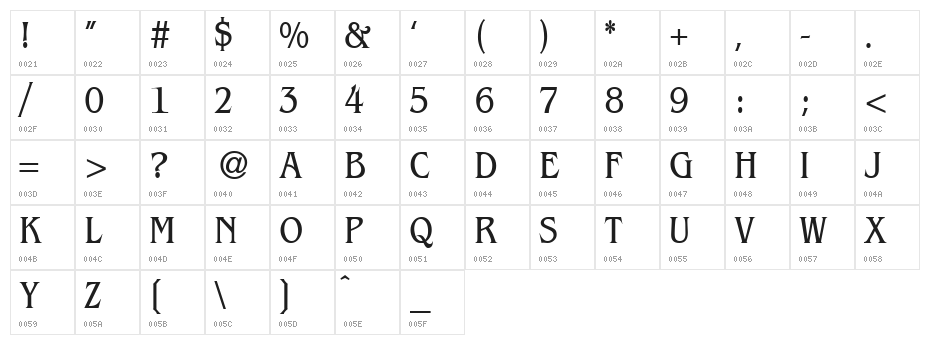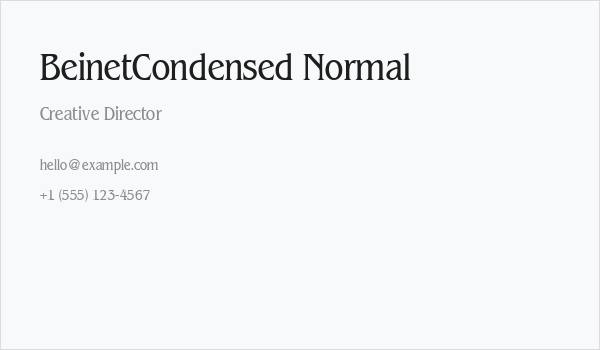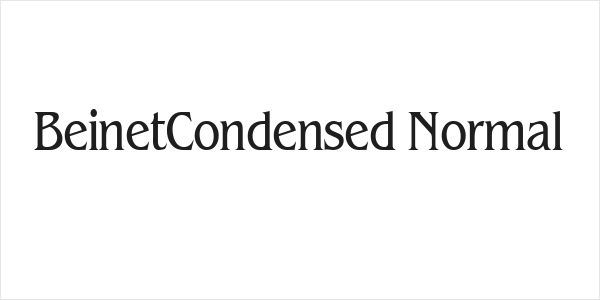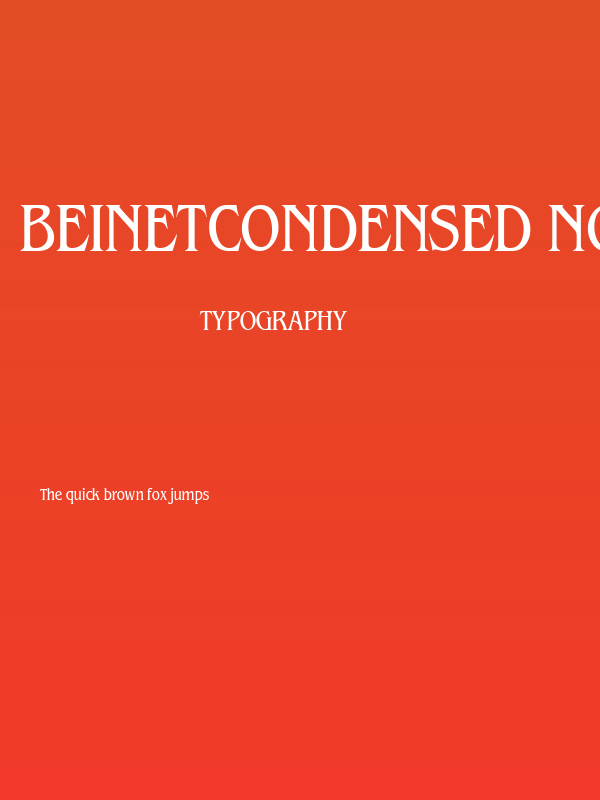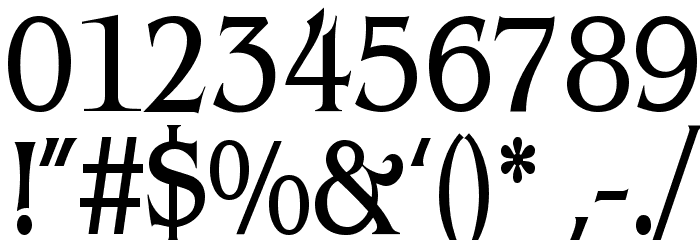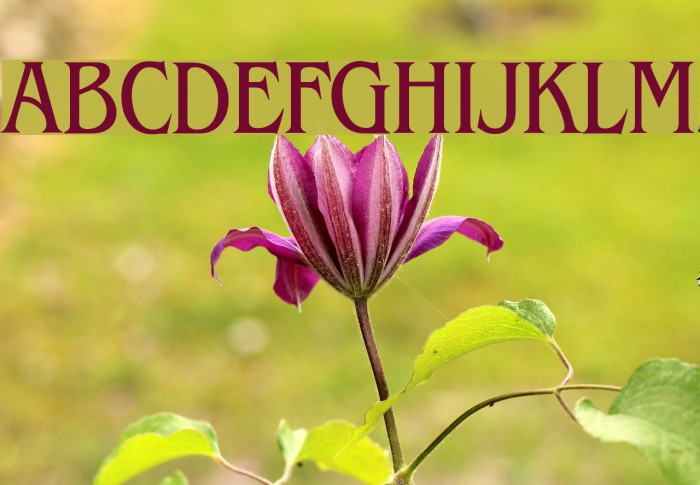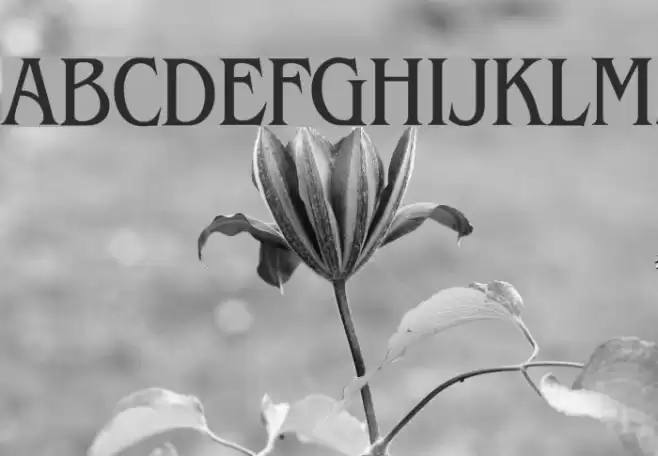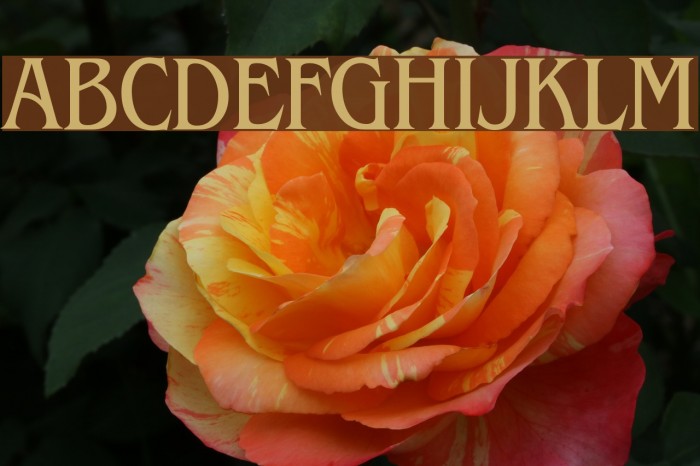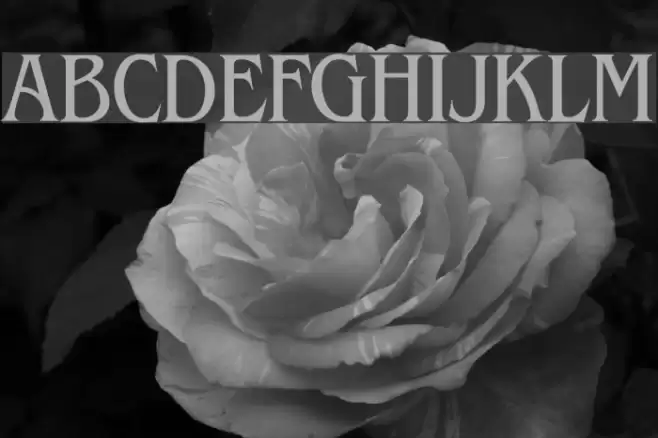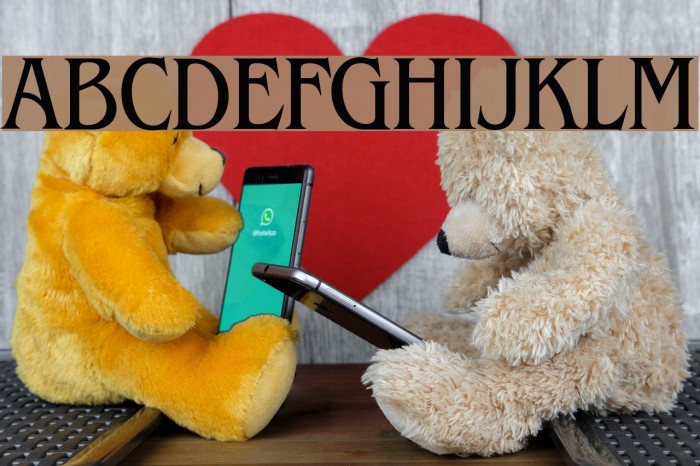
BeinetCondensed Normal Font
| Projetos propostos | Ideal for book covers, formal invitations, editorial layouts, and branding materials that require a touch of elegance. |